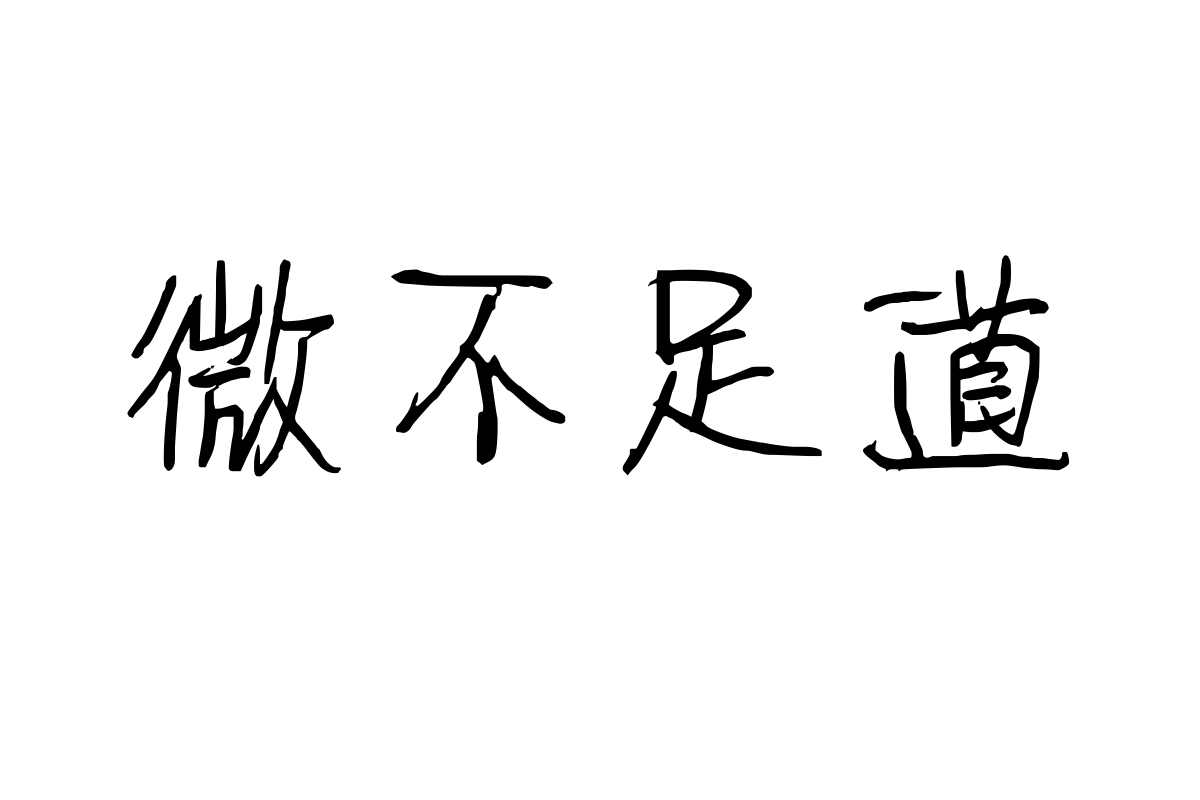
蝉羽露露午茶体是一款具有独特风格的中文字体,其特点如下:
1. 字形结构:蝉羽露露午茶体的字形结构简洁明了,笔画流畅自然。整体字形呈现出一种轻盈、灵动的感觉,给人一种清新脱俗的视觉体验。
2. 字体风格:该字体采用了现代简约的设计风格,线条粗细适中,没有过多的装饰元素。整体风格简洁大方,适合用于各种商业、办公、设计等领域的文本展示。
3. 应用场景:蝉羽露露午茶体适用于需要突出文字美感和设计感的场景,如广告宣传、产品包装、网页设计等。同时,也适用于需要展现个性和创意的场合,如个人博客、社交媒体等。
总之,蝉羽露露午茶体是一款简约而不失个性的中文字体,适用于多种应用场景,具有较高的实用性和可定制性。